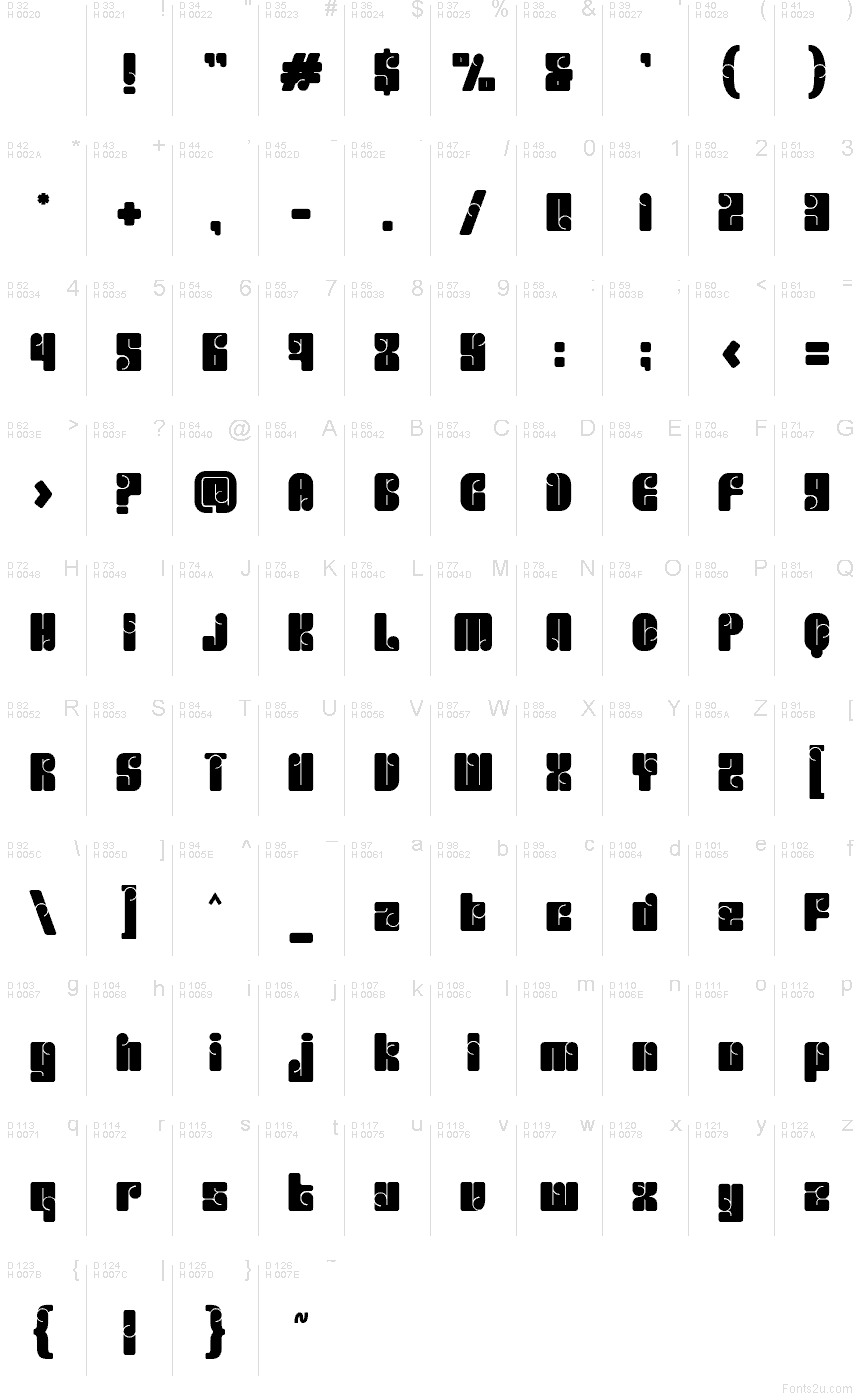
Dynamic Display Two od Putracetol Studio je bezplatné dekorativní písmo typu display, definované podsaditými zaoblenými tvary a hlubokými zářezy, díky kterým litery působí jako vyřezané z měkkých obdélníkových bloků. Tato opakující se silueta vytváří kompaktní, až skládačkový rytmus, zatímco zakřivené výřezy a čisté spoje brání tomu, aby písmo působilo jen jako obyčejný geometrický styl.
Nejlépe vynikne na plakátech, hudebních vizuálech, titulcích, obalech a v hlavičkách sociálních sítí, kde krátká slova potřebují výraznou grafickou podobu. Bloková hmotnost dodává velkým nápisům skutečnou váhu a tyto hluboké výřezy zajišťují dostatek pohybu pro loga, samolepky a branding, který chce působit spíše hravě než formálně.